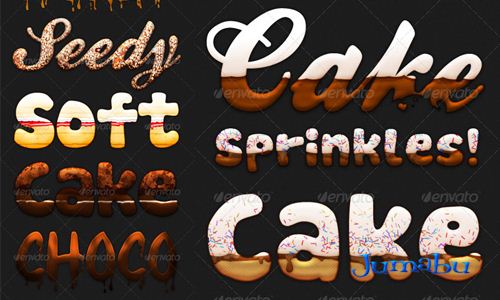
Descarga estas tipografías con decoraciones de dulces
Herrrrmosos estilos en photoshop que casi vienen con olor a tortas dulces,
texturas de donuts o esas famosas cakes que suelen comer en el norte de nuestro
continente. Están re buenos y con un estilo espectacular! Alta calidad!